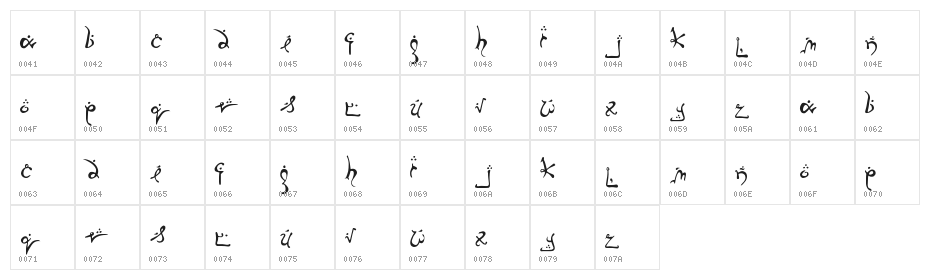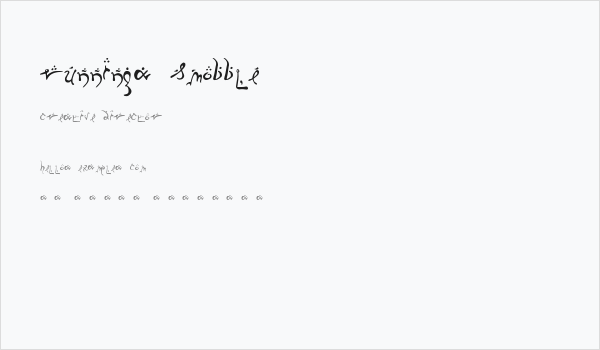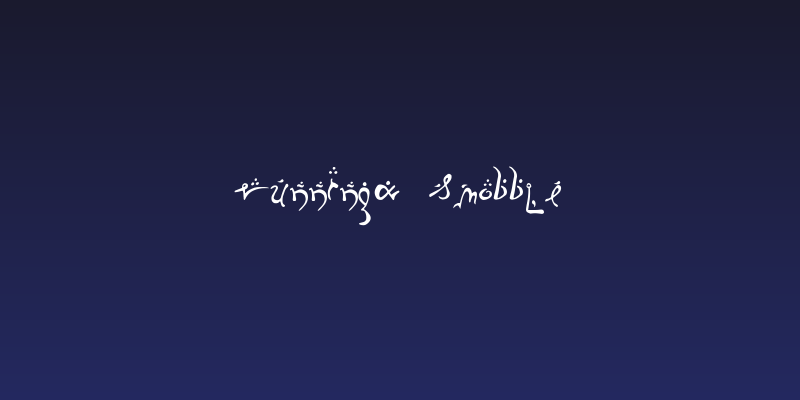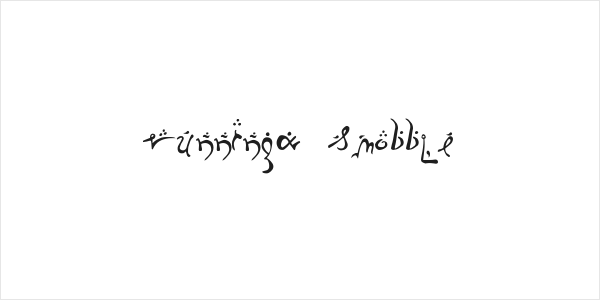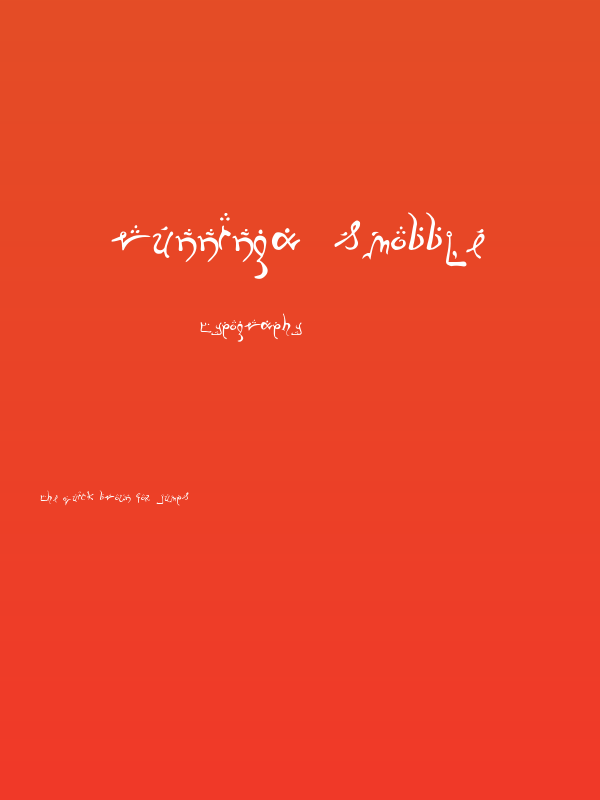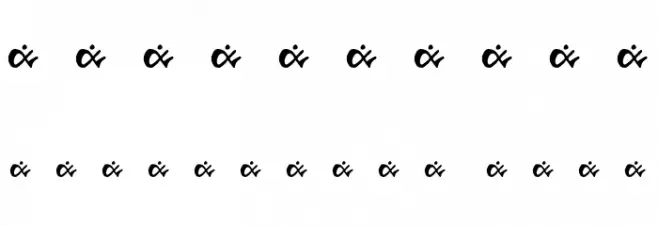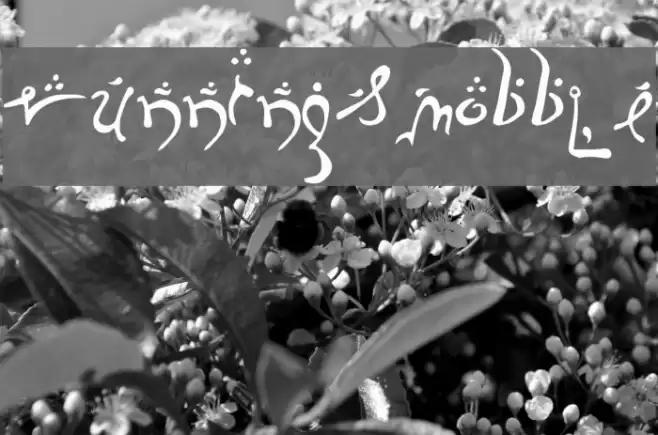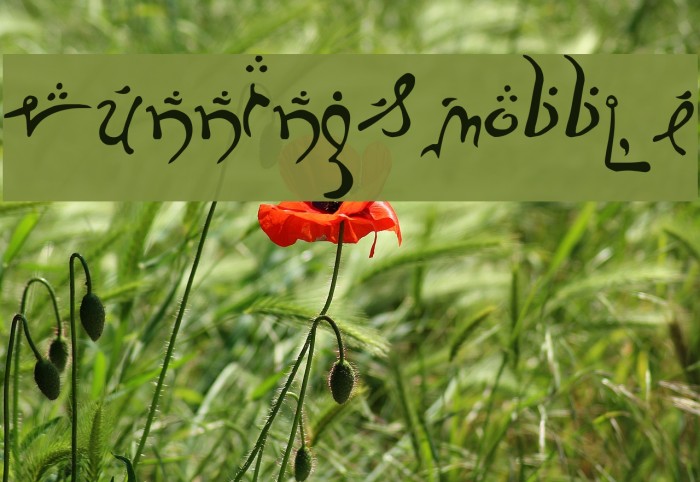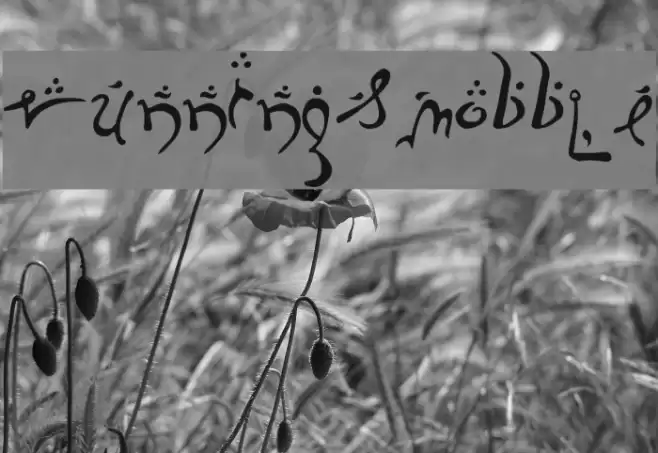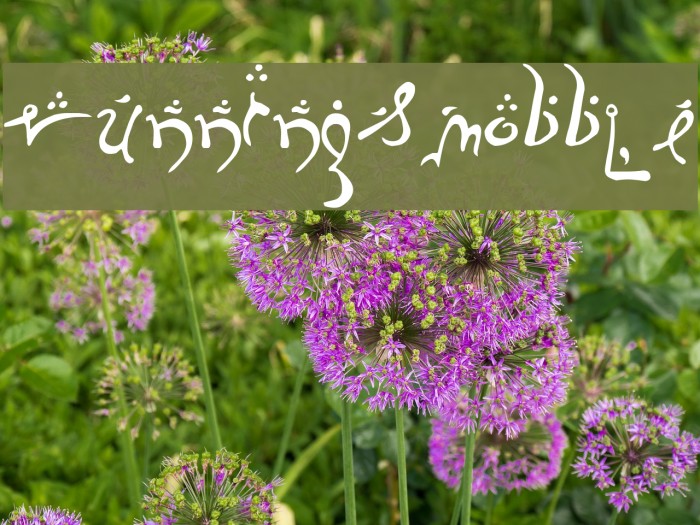
Running-Smobble Font
| Общий стиль | Whimsical and Artistic |
| Область применения | Headlines, Artistic projects, Branding |
| Рекомендуемые проекты | Ideal for creative projects such as children's books, greeting cards, artistic posters, and branding for playful or whimsical products. |